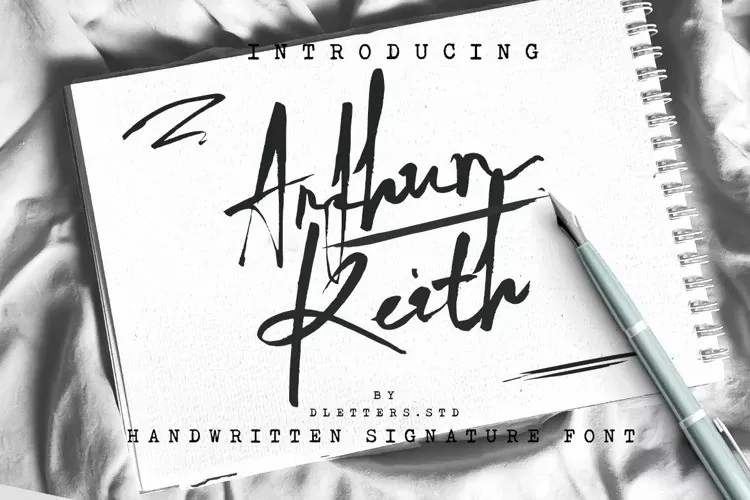
Esta é uma nova tipografia de script feita por mãos habilidosas que a deixam muito refinada. Este tipo de letra foi criado com gosto notável e com toques clássicos, tem muitas ligaturas, SAlt e Swash para manter o ar natural da fonte, sendo ao mesmo tempo fácil de ler, elegante, estilosa e atrativa. Estamos convencidos de que esta tipografia ficará perfeitamente em sintonia com qualquer projeto, seja ele digital ou impresso. Ideal tanto para aplicações profissionais quanto para criação de materiais gráficos pessoais, a fonte Arthur Keith é uma escolha inteligente. Seja o seu próximo design mais sofisticado ou um simples efeito editorial em suas produções digitais, essa tipografia fará toda a diferença.